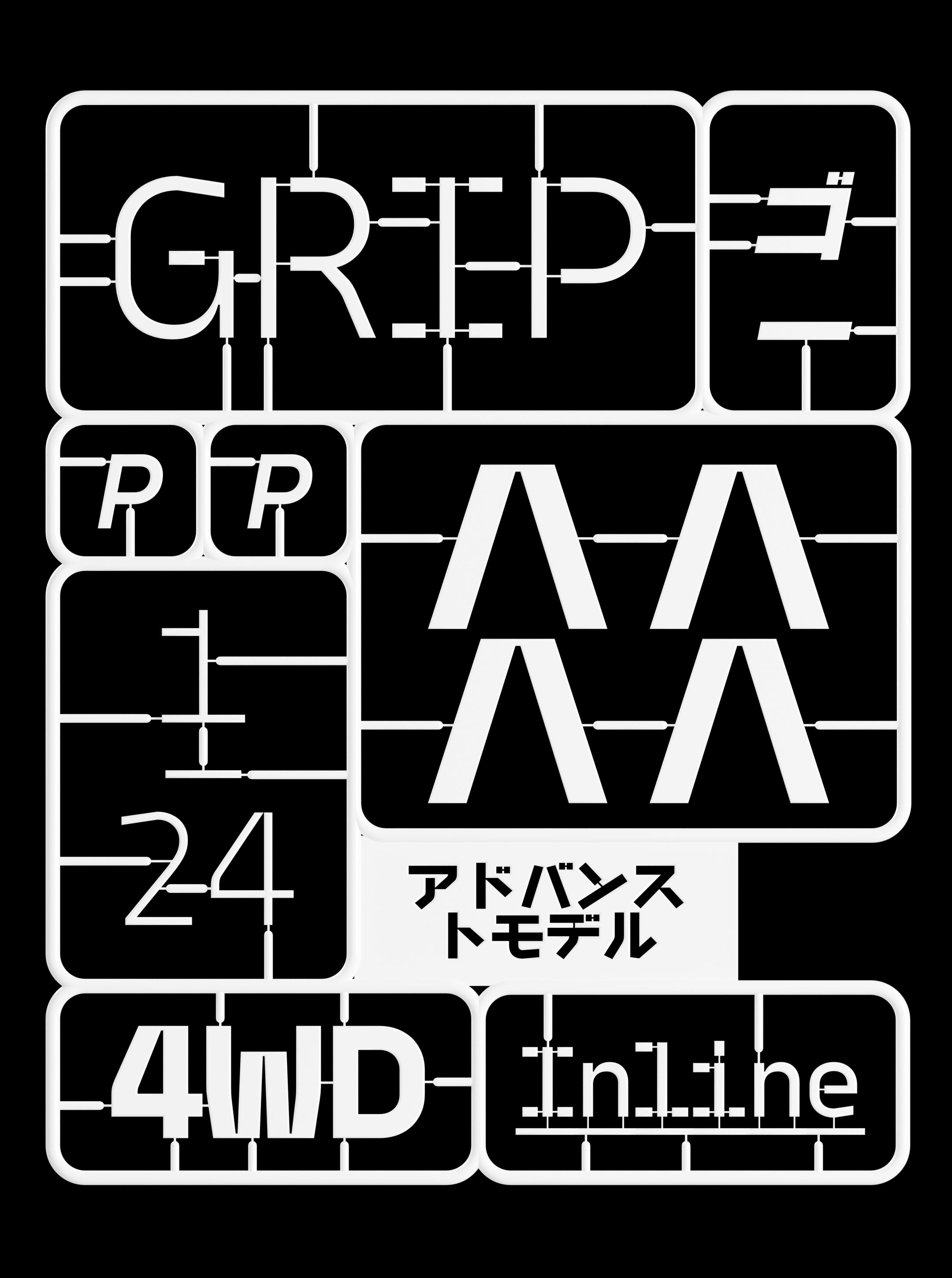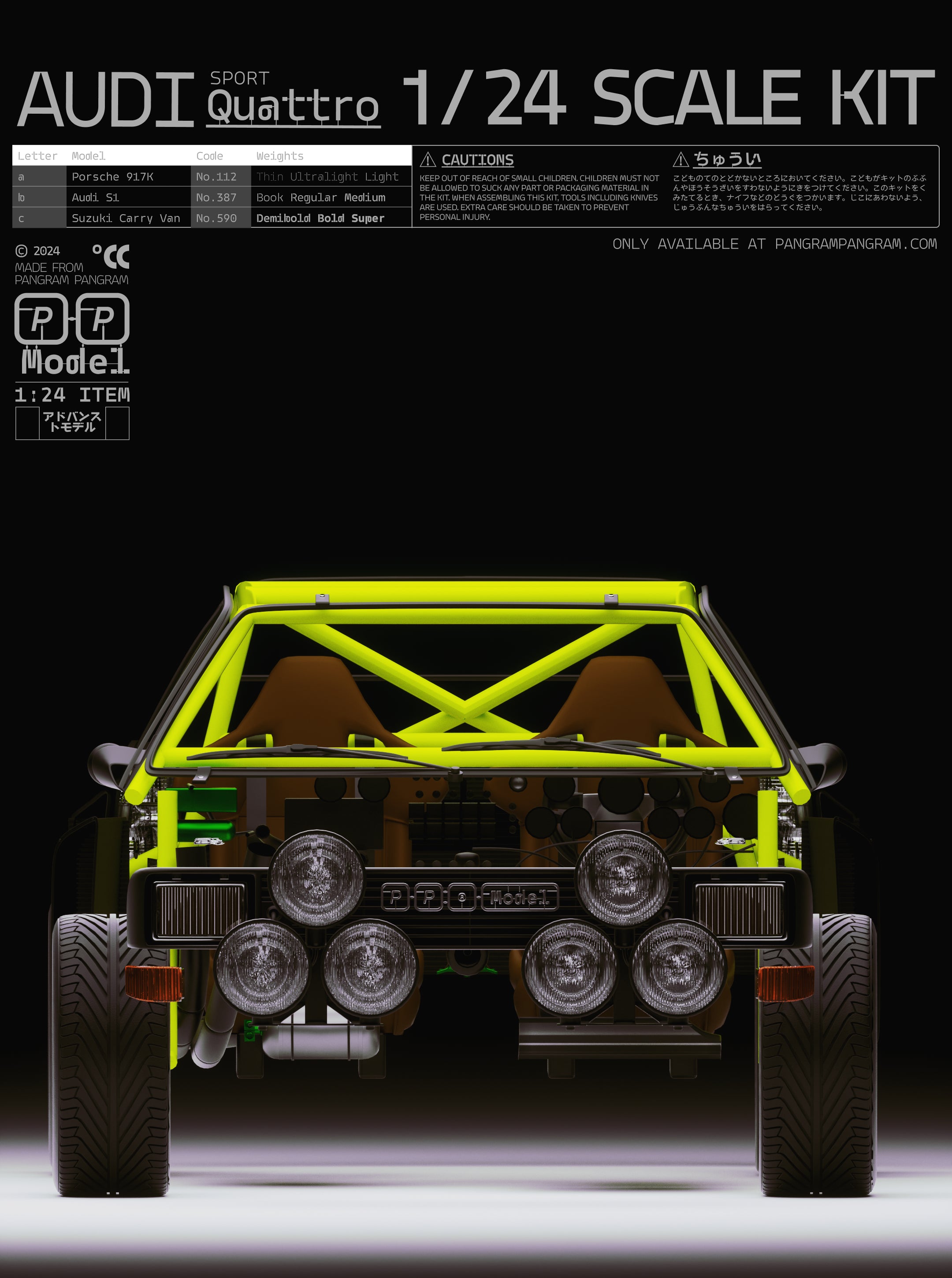
Model Mono
Model rend hommage au monde des maquettes en plastique, s'inspirant de la marque japonaise emblématique Tamiya.
Fonctionnalités de Model Mono
Inspiré de la marque japonaise emblématique Tamiya.
Model rend hommage à l'univers des maquettes en plastique, s'inspirant de l'emblématique marque japonaise Tamiya. Mondialement reconnue pour ses kits d'assemblage extrêmement détaillés et précis, l'héritage de Tamiya sert de base à ce design, célébrant l'art méticuleux du modélisme. La police allie nostalgie et précision moderne, capturant l'essence du processus d'assemblage grâce à ses formes épurées et modulaires et à son esthétique mécanique.
PP Model propose quatre familles, de la version Model par défaut aux variantes à chasse fixe et aux styles expérimentaux Plastic. Son design stimule la créativité, offrant des options typographiques qui incarnent le concept à différents niveaux, imitant les composants connectés des maquettes dans leurs formes. Au total, la police comprend 72 polices, disponibles en styles droit et italique, avec une prise en charge Extended du latin, des alphabets japonais Hiragana et Katakana, de la ponctuation japonaise et des caractères de mesure rares.
4 sous-familles x 18 styles avec 626 glyphes chacune
avec Italiques
Avec Kana, Hiragana et Katakana